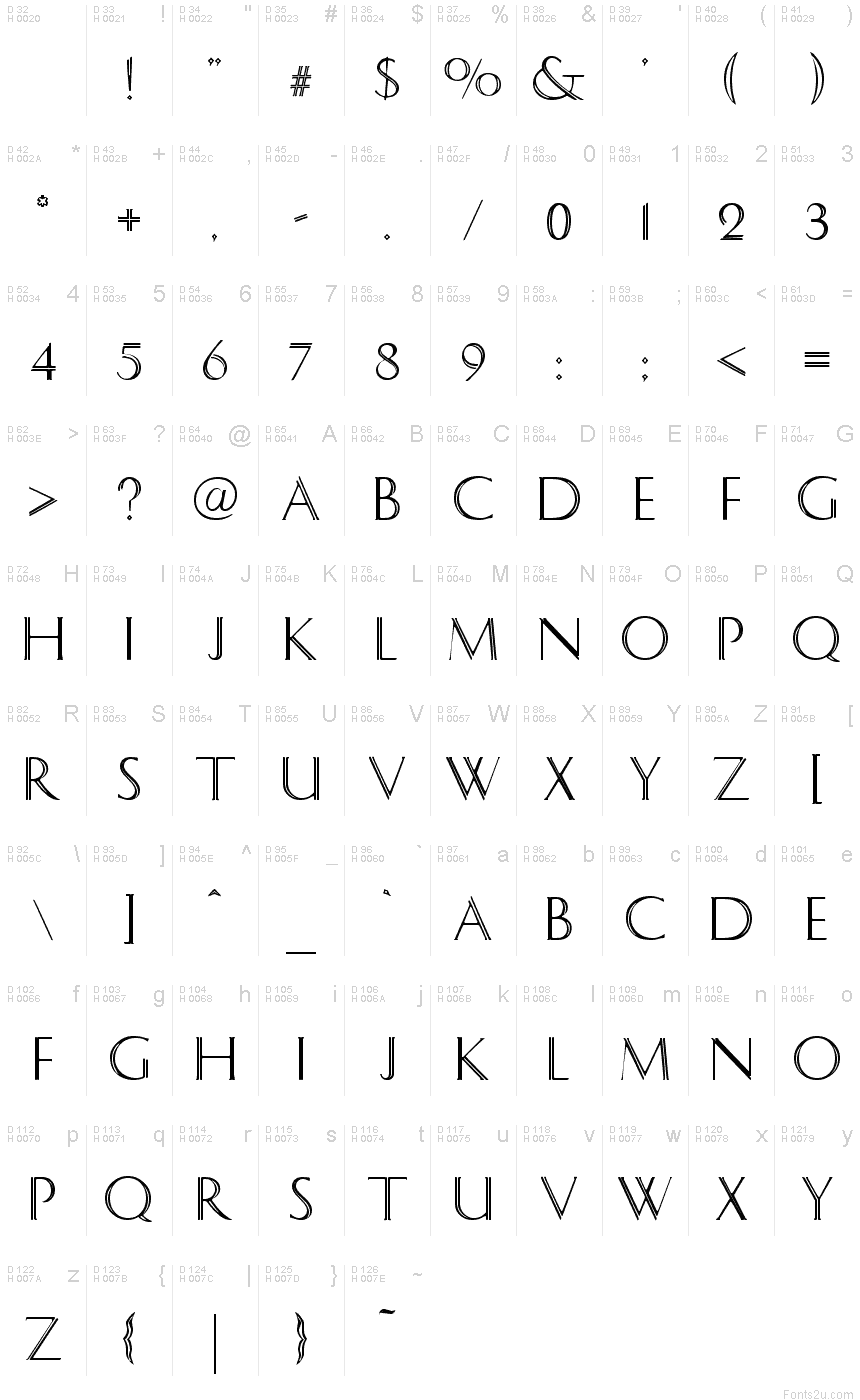
Caesar to bezpłatny, dekoracyjny krój pisma w stylu retro, który łączy elegancję Art Déco z nutą klasycznego Rzymu. Wysokie, wąskie kapitałki i dwuliniowe pociągnięcia przypominają grawerowany metal – są ostre, chłodne i lekko teatralne – podczas gdy luźne światło między znakami zapewnia czytelność bez wrażenia przesytu. Rytm równoległych linii dodaje subtelnego blasku, sprawiając, że nawet krótkie słowa wyglądają jak tytuły filmowe.
Zastosowanie Caesar na plakatach, logo, etykietach win, okładkach książek, zaproszeniach i eleganckich opakowaniach błyskawicznie nadaje im kinowy, vintage'owy sznyt. Ten darmowy font świetnie sprawdza się w szyldach, menu i nagłówkach, gdzie zależy Ci na wyrafinowaniu bez sztywności. Używaj Caesar w dużym rozmiarze, aby uzyskać maksymalny efekt, a w tekstach głównych połącz go z prostym, nowoczesnym bezszeryfowym krojem, by pozwolić jego ozdobnym literom grać pierwsze skrzypce.